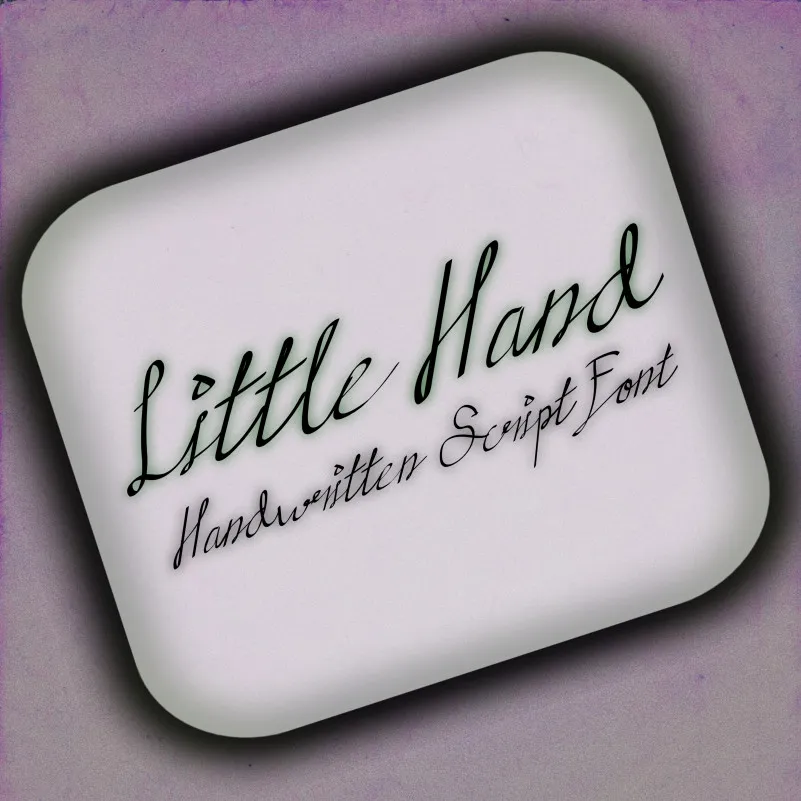
Little hands Handwritten Font – Download Grátis
Baixar a fonte “Little hands Handwritten Font” é uma ótima escolha para aqueles que valorizam o charme dos traços humanizados no design digital. Sua descrição original, cuidadosamente desenvolvida pelo designer chasim, nos permite entender os detalhes e as características únicas desta fonte. A Little hands Handwritten Font é uma preciosidade criada em estilo livre e natural, recheada de nuances que remetem à escrita feita a mão. A cada caractere desse sistema fontes apresenta traços suaves, sublinhados naturais e um arco levemente ondulado, o que a torna perfeita para aplicar em design gráfico como cartazes de marketing, publicações de jornal ou até mesmo ilustração digital. Com uma aparência amigável e acessível, esta fonte também é adequada para criações mais elaboradas, como logotipos empresariais ou até mesmo letras do vídeo que precisam transmitir um estilo casual e pessoal, sem perder a elegância necessária para seu uso final. Por último mas não menos importante, ao utilizar essa fonte, você concorda com as regras estabelecidas na licença de utilização do produto. Este é mais uma maneira da chasim de garantir que todos os usuários das ferramentas que criou se comprometam a manter o espírito genuinamente original e autêntico da Little hands Handwritten Font.